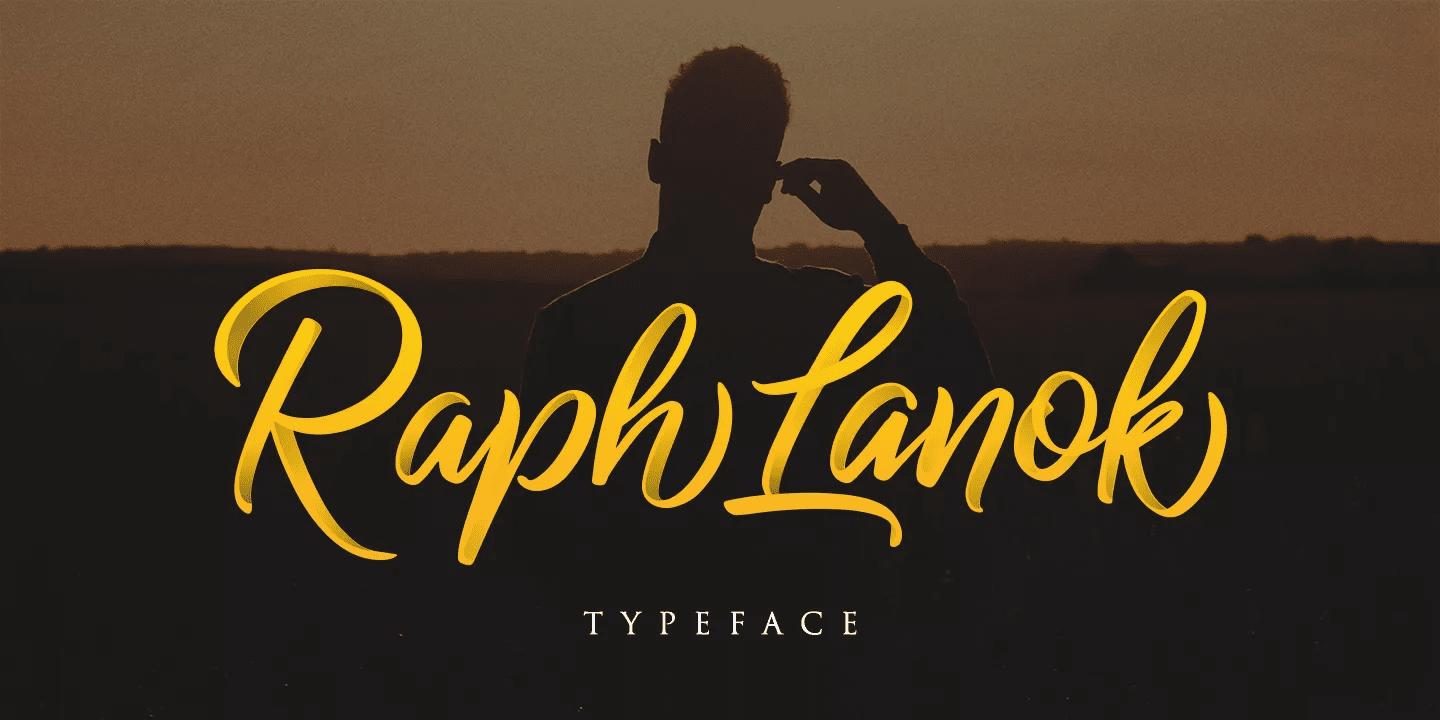
Название: Raph Lanok Font
Представляем вашему вниманию шрифт Raph Lanok Typeface с элегантным стилем ручной кисти для надписей. Поэтому он выглядит естественно, как ручная работа, потому что у семьи Raph Lanok больше выбора персонажей. Этот шрифт лучше всего использовать для вашего дизайнерского проекта, в котором есть концепция веселья, смелости и спортивности. Также может быть применен для дизайна логотипа, заголовочного сайта, сделать несколько шрифтов для цитаты, дизайна футболок и т.д.
Raph Lanok имеет три стиля шрифта, похожие, но разные, а именно: Raph Lanok Future и Raph Lanok Rusty, но вы также получите Raph Lanok Swash из линии быстро чистится, как с помощью шрифта.
Шрифт Raph Lanok Typeface заслуживает того, чтобы стать одной из ваших коллекций шрифтов, потому что он уникален и имеет множество вариантов альтернативных глифов.
Название: Raph Lanok Font
Представляем вашему вниманию шрифт Raph Lanok Typeface с элегантным стилем ручной кисти для надписей. Поэтому он выглядит естественно, как ручная работа, потому что у семьи Raph Lanok больше выбора персонажей. Этот шрифт лучше всего использовать для вашего дизайнерского проекта, в котором есть концепция веселья, смелости и спортивности. Также может быть применен для дизайна логотипа, заголовочного сайта, сделать несколько шрифтов для цитаты, дизайна футболок и т.д.
Raph Lanok имеет три стиля шрифта, похожие, но разные, а именно: Raph Lanok Future и Raph Lanok Rusty, но вы также получите Raph Lanok Swash из линии быстро чистится, как с помощью шрифта.
Шрифт Raph Lanok Typeface заслуживает того, чтобы стать одной из ваших коллекций шрифтов, потому что он уникален и имеет множество вариантов альтернативных глифов.